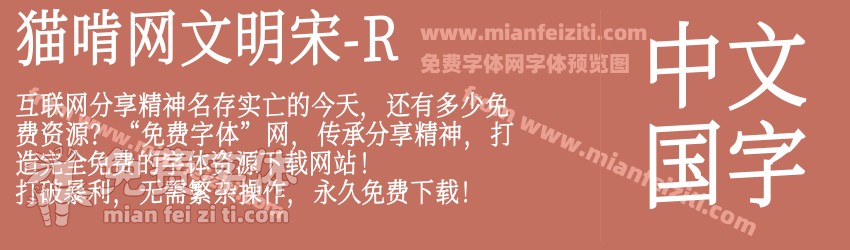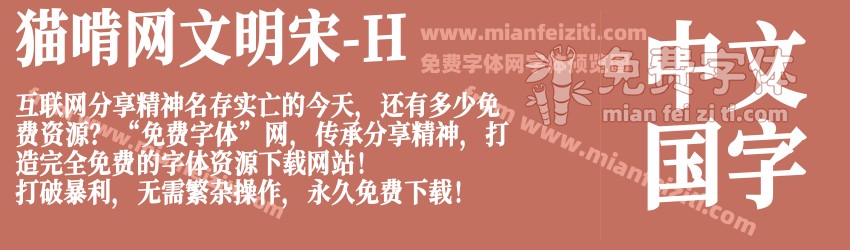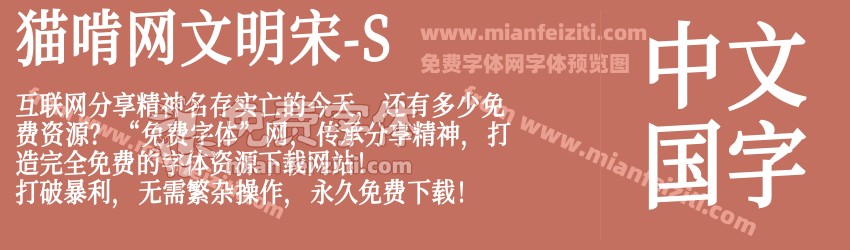
猫啃网文明宋-个人改造的基于思源的免费商用宋体字字体资讯
猫啃网文明宋是猫啃网改造的系列免费商用字体,属于宋体字,一共6个字重,字体效果如下图:
可以看到,该字体属于比较常规的宋体,中规中矩的字形很适合日常显示或者打印使用,因为该字体基于思源免费字体改造,也是属于可以免费商用的字体,在免费字体网可以免费下载到!